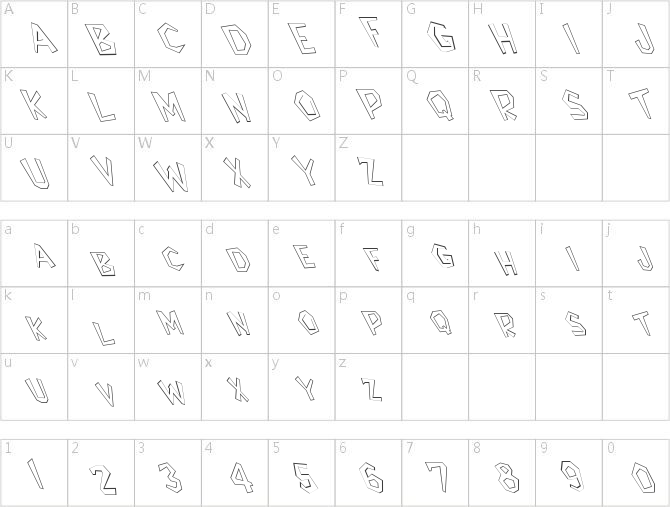
FZ JAZZY 8 HOLLOW LEFTY 詳情頁
FZ JAZZY 8 HOLLOW LEFTY字體字庫是一款讓人賞心悅目、百看不厭的英文字體,適合各類廣告和產(chǎn)品包裝設(shè)計應(yīng)用,字體大小0.04MB,格式為ttf字體,上傳用戶是sygyve520,作者/版權(quán)方為未知